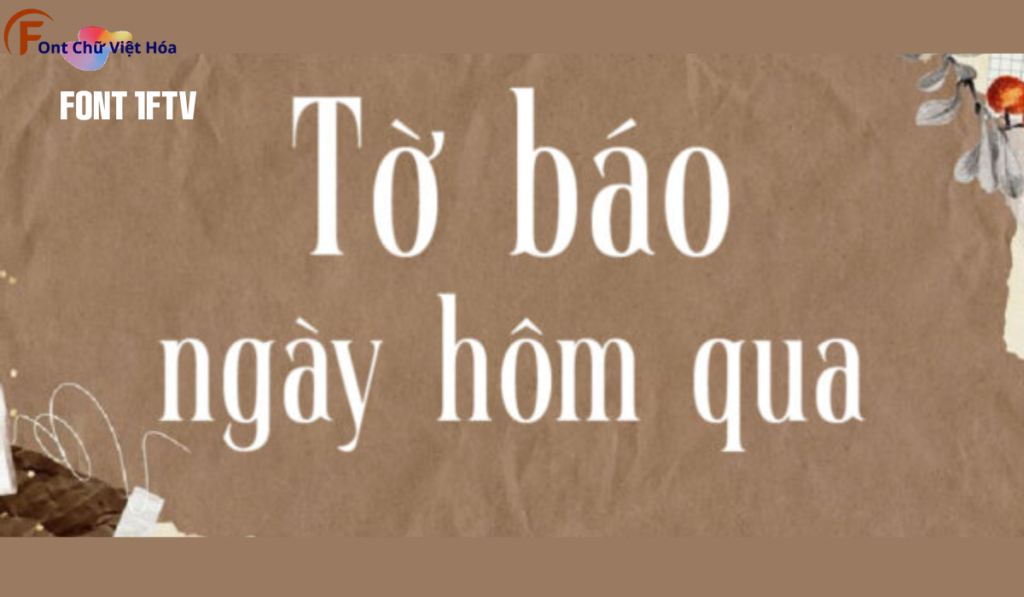
Font 1FTV East Gravton
Tác giả: 1FTV Design
Font 1FTV East Gravton là một font chữ độc đáo, thuộc bộ 1FTV, nổi bật với phong cách sans-serif hiện đại và các đường nét mạnh mẽ, cá tính. Thiết kế của 1FTV East Gravton tập trung vào sự rõ ràng và dễ đọc, đặc biệt phù hợp cho các thiết kế đòi hỏi tính thẩm mỹ cao như poster, logo, và tiêu đề. Với tỷ lệ chữ cân đối và các đường nét đậm, font này tạo ra ấn tượng thị giác mạnh mẽ và giúp tối ưu hóa không gian trong thiết kế. Font này cũng đã được Việt hóa, mang đến sự linh hoạt và tiện dụng cho các dự án thiết kế bằng tiếng Việt.